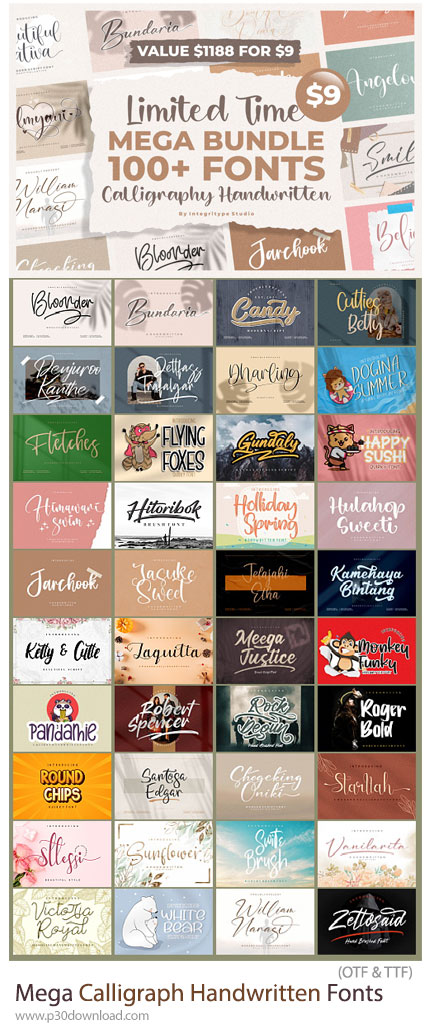
دانلود Mega Calligraph Handwritten Fonts Bundle مجموعه فونتهای دستنویس و خوشنویسی انگلیسی
اگر به دنبال مجموعهای فوقالعاده از فونتهای دستنویس زیبا، ظریف و مناسب طراحیهای مدرن هستید، این باندل دقیقاً همان چیزی است که نیاز دارید و با فرمت های OTF و TTF بر روی سایت برای دانلود قرار گرفته است. این پک شامل مجموعهای بزرگ از فونتهای خوشنویسی دستنویس است که با سبکهای متنوع طراحی شدهاند تا به پروژههای شما حس اصالت، زیبایی و لطافت ببخشند. این بسته برای طراحان گرافیک، تولیدکنندگان محتوا، برندها، طراحان لوگو، طراحان کارت دعوت، پوستر، بستهبندی و حتی شبکههای اجتماعی فوقالعاده کاربردی است. با تهیه این باندل، شما به یک مجموعه عظیم از فونتهای زیبا با هزینهای بسیار کمتر از خرید تکی دسترسی خواهید داشت. تنوع فوقالعاده بالا باعث میشود برای هر پروژهای یک سبک مناسب پیدا کنید و طراحیهایتان حرفهایتر از همیشه بهنظر برسند.